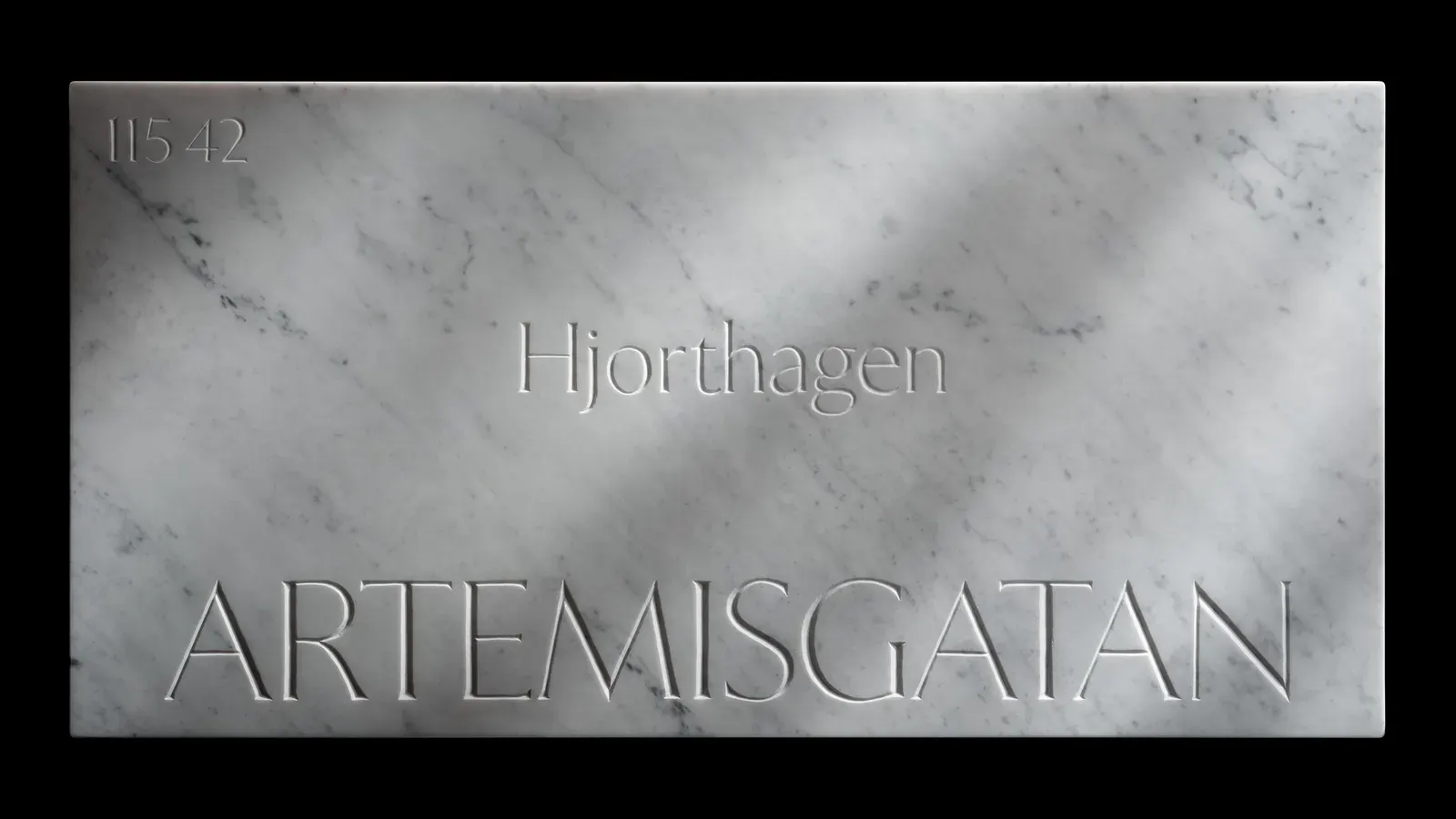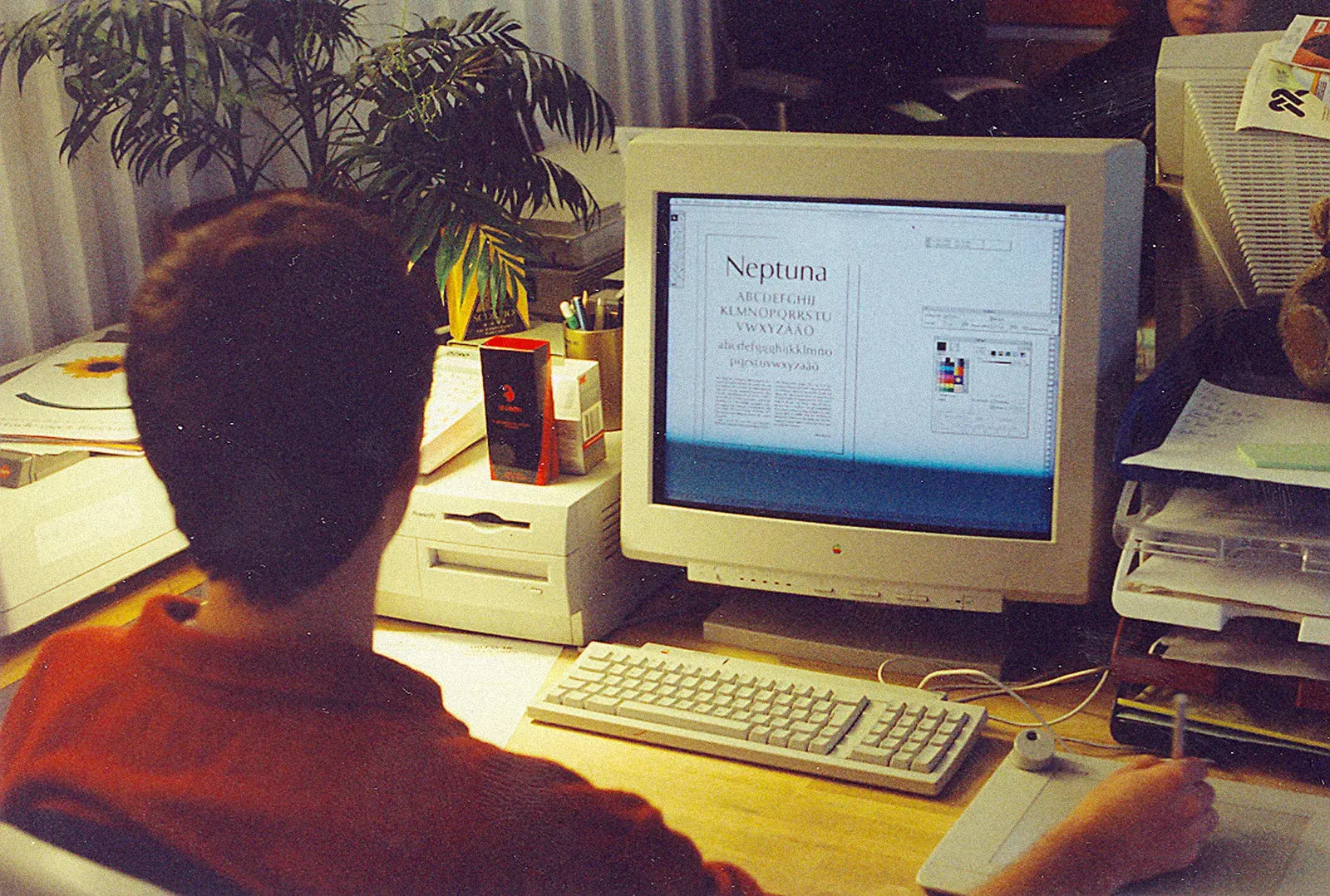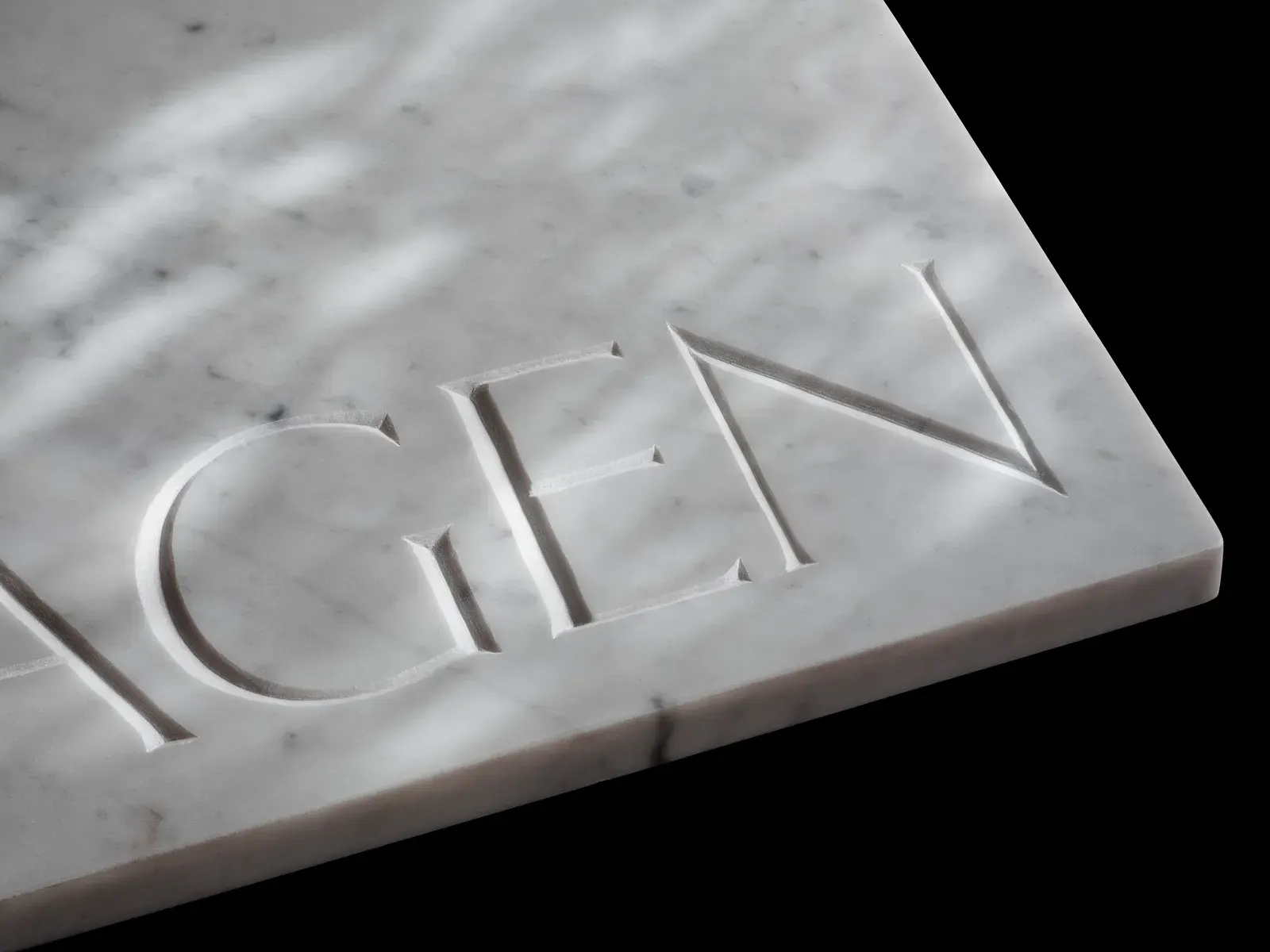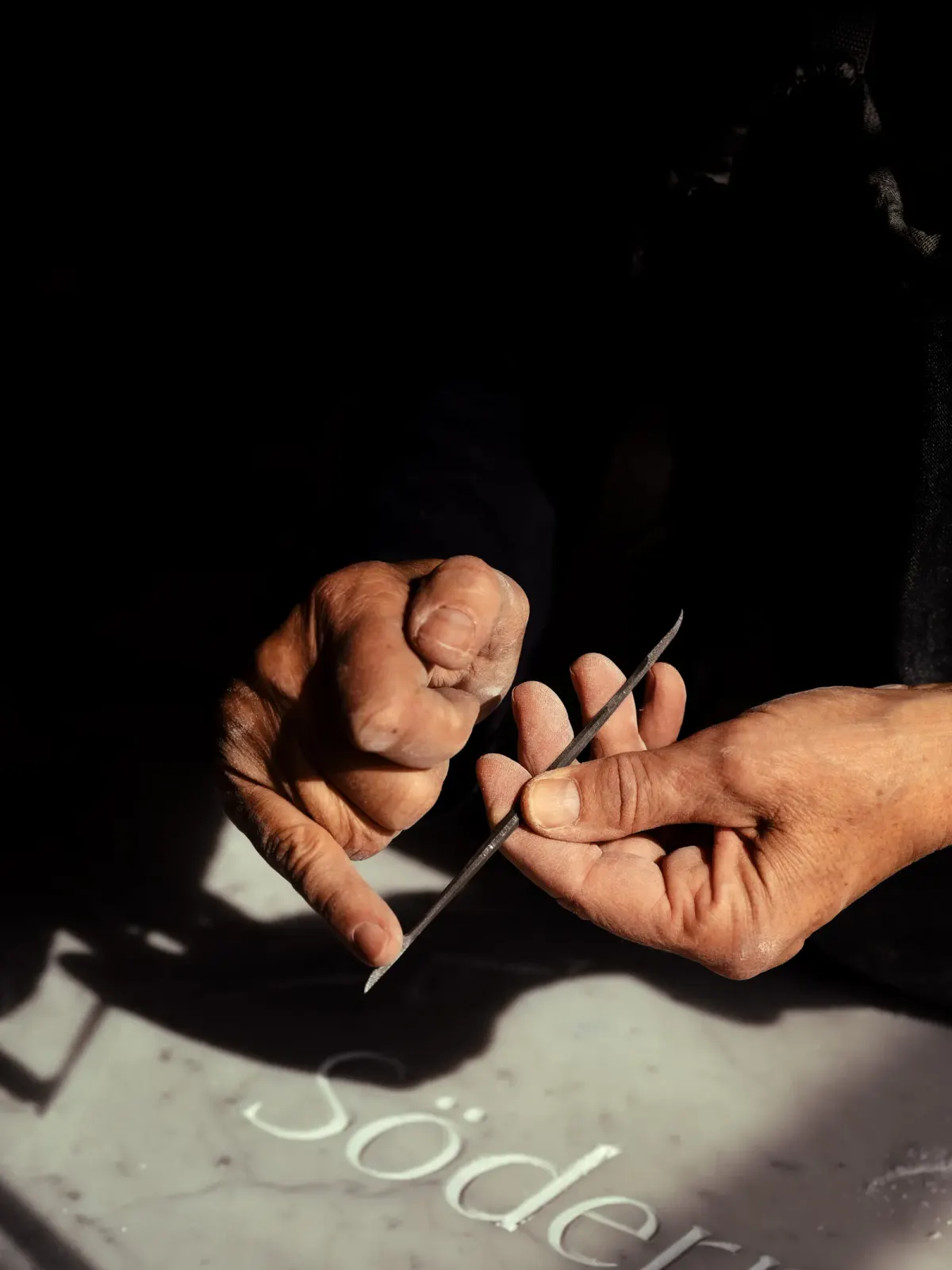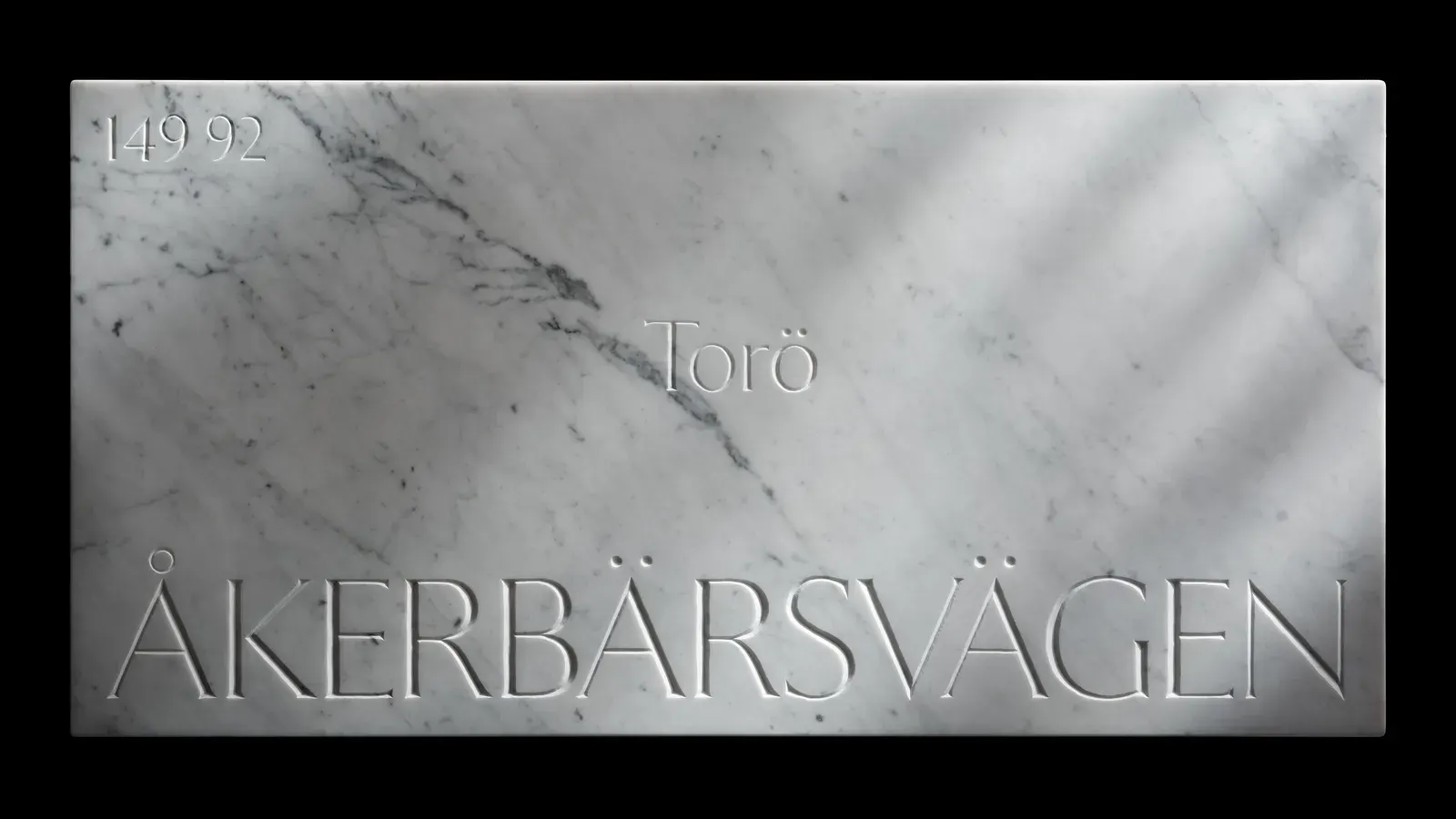
ในเมืองเล็ก ๆ ชื่อเปียตราซานตา ทางตอนเหนือของอิตาลี มีป้ายชื่อถนนหินอ่อนแผ่นหนึ่งวางพิงอยู่บนโต๊ะช่าง ตัวอักษรบนนั้นสะกดว่า ÅKERBÄRSVÄGEN ซึ่งเป็นชื่อถนนบนเกาะเล็ก ๆ ในสวีเดน ห่างจากที่ที่มันถูกแกะไปเกือบสองพันกิโลเมตร ป้ายแผ่นนี้ไม่ได้ทำไว้ติดถนน มันทำไว้เพื่อประกาศว่าฟอนต์ชื่อ Exemplar ทำเสร็จแล้ว หลังจากเริ่มวาดมาตั้งแต่ปี 1994
คนวาดชื่อ Göran Söderström เจ้าของโรงหล่อฟอนต์ Letters from Sweden ที่สตอกโฮล์ม สามสิบสองปีที่ผ่านมาเขาไม่ได้นั่งวาดตัวนี้ตัวเดียวตลอดเวลา แต่กลับมาหามันใหม่ทุกสิบกว่าปี แล้วแต่ละครั้งก็ได้ฟอนต์ที่ไม่เหมือนเดิมเลย
เวอร์ชันแรกชื่อ Neptuna และมันอยากเถียง
ปี 1994 เขานั่งวาดอยู่หน้าเครื่อง Power Macintosh 7100 ในห้องที่ถนนเกิทกาทัน ย่านเซอเดอร์มาล์ม ตอนนั้นฟอนต์ตัวนี้ยังชื่อ Neptuna ยุคนั้นคือยุคที่นิตยสาร Ray Gun กับโรงหล่อ Emigre กำลังรื้อทุกกฎของการเรียงพิมพ์ทิ้ง งานที่ออกมาจากมือคนอายุยี่สิบกว่าจึงเป็นแบบที่ทางเว็บของโปรเจกต์เขียนไว้ตรง ๆ ว่าเป็นฟอนต์ที่อยากชนะการเถียง ทุกรายละเอียดถูกดันไปไกลกว่าที่จำเป็น
อ่านแล้วน่าจะคุ้น ใครที่เคยเปิดไฟล์งานตัวเองเมื่อสิบปีก่อนน่าจะเข้าใจ
ปี 2008 เขาเอากลับมาวาดใหม่ เปลี่ยนชื่อเป็น Exemplar Pro แล้วปล่อยผ่านโรงหล่อ PSY/OPS ครั้งนี้มีคนอื่นเข้ามาช่วยดูด้วย สิ่งที่หายไปคือความล้นทั้งหลาย สิ่งที่รอดมาคือไอเดียที่ทนต่อการถูกเถียงกลับได้จริง เวอร์ชันนั้นไปโผล่บนแสตมป์ และบนงานอัตลักษณ์ของมหาวิทยาลัย Hamad Bin Khalifa ที่กาตาร์
เวอร์ชันที่สามไม่เถียงแล้ว
สิบเจ็ดปีถัดมาเขากลับมาอีกรอบ รอบนี้เขาบอกว่าเป็นเรื่องของการปล่อยมากกว่าการสร้าง ผลลัพธ์คือ Exemplar ปี 2026 ห้าน้ำหนักพร้อมตัวเอียงครบ 1,018 อักขระ รองรับ 370 ภาษา และมีถึงสี่ระบบตัวเขียนคือละติน ซีริลลิก กรีก และอาหรับ
สองระบบหลังไม่ได้มาจากมือเขา ตัวกรีกวาดโดย Laurette Colmard ส่วนตัวอาหรับวาดโดย Léo Guibert ซึ่งแปลว่าฟอนต์ที่เริ่มจากคนคนเดียวในห้องเช่า ตอนจบกลายเป็นงานที่ต้องมีคนอื่นถึงจะครบ
ทำไมต้องเอาไปสลักหิน
ป้ายที่ทำมีสามแผ่น แผ่นละหนึ่งที่อยู่ คือถนนที่เขาวาดเวอร์ชันแรก ถนนที่เขาวาดเวอร์ชันสอง และถนนที่เขาวาดเวอร์ชันสุดท้าย พูดอีกอย่างคือทำแผนที่ชีวิตตัวเองด้วยชื่อถนนสามชื่อ
งานแกะทำที่เปียตราซานตา เมืองที่ชื่อแปลว่าหินศักดิ์สิทธิ์ อยู่เชิงเขาอัลปีอาปวาเน ที่ที่มีเกลันเจโลเคยมาเลือกหินเมื่อห้าร้อยปีก่อน เครื่องมือที่ช่างใช้ยังเป็นสามชิ้นเดิม คือ subbia กับ gradina กับ scalpello สิ่วปลายแหลม สิ่วซี่ฟัน และสิ่วปลายแบน
มือที่แกะเป็นของ Barbara Adamsky ช่างปั้นชาวเยอรมันที่ย้ายมาอยู่อิตาลีตั้งแต่ปี 1987 เรียนจบจากสถาบันศิลปะที่คาร์ราราแล้วอยู่ในวงการนี้มาตลอด การแกะตัวอักษรลงหินมีวิธีของมัน คือถือสิ่วเอียงทำมุม แล้วเซาะร่องเป็นรูปตัววี เพื่อให้แสงเข้ามุมหนึ่งแล้วเกิดเงาอ่านออก เซริฟหนึ่งอันใช้เวลาพอ ๆ กับเส้นโค้งหนึ่งเส้น
ข้อที่ต่างกันชัดที่สุดระหว่างหินกับไฟล์ คือหินไม่มีปุ่มย้อนกลับ ตีผิดหนึ่งครั้งก็คืออยู่กับมันไปตลอด ส่วนงานดิจิทัลมีปัญหาตรงข้าม คือย้อนได้ไม่จำกัด แปลว่าไม่มีอะไรจบจนกว่าเราจะเป็นคนบอกเองว่าจบ
สามสิบสองปีของ Exemplar คือเรื่องนี้ทั้งเรื่อง มันไม่ได้ถูกวาดนานขนาดนั้นเพราะยาก มันนานขนาดนั้นเพราะไม่มีอะไรมาบังคับให้หยุด การเอาไปสลักหินคือวิธีบอกตัวเองว่าพอแล้ว
เรื่องฟอนต์กับหินไม่ได้เพิ่งเกิด เราเคยเขียนถึงOptima ที่ Hermann Zapf ร่างตัวแรกจากป้ายหินอ่อนในสุสานที่ฟลอเรนซ์ ต่างกันตรงที่ Optima เอาหินมาเป็นต้นทาง ส่วน Exemplar เอาหินไปไว้ตอนจบ
ชาวโรมันมีประโยคหนึ่งว่า littera scripta manet ตัวหนังสือที่เขียนแล้วยังอยู่ พวกเขาพูดตอนที่ยังไม่มีใครรู้จักไฟล์ที่เปิดไม่ได้เพราะเวอร์ชันโปรแกรมไม่ตรงกัน
เราเลยอยากถามต่อว่า ถ้างานที่เราทำอยู่วันนี้ต้องถูกเลือกมาแค่ชิ้นเดียวเพื่อเอาไปตีลงหิน จะเลือกชิ้นไหน และจะกล้าตีจริงไหม